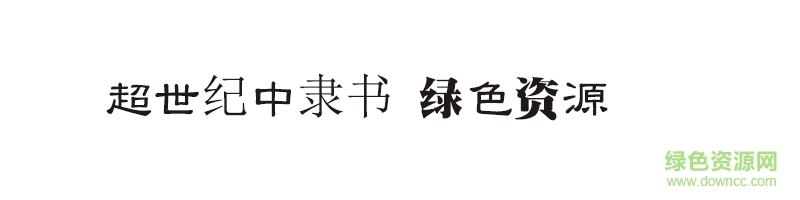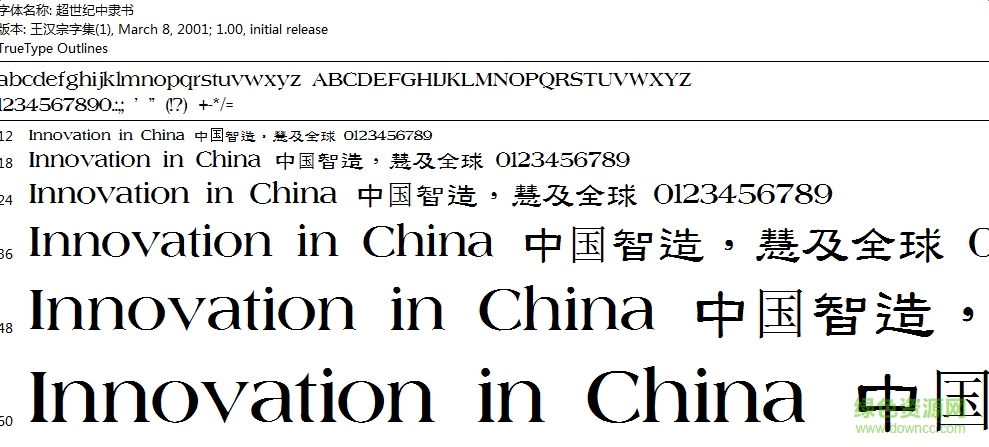
超世紀(jì)中隸字體是一款形體勻逼齊整、字體比較容易書寫的標(biāo)準(zhǔn)字體。它是大篆由隸、楷之間的過渡而來,非常受用戶的喜愛!對(duì)自己寫字字體不滿意的朋友們可以來綠色資源網(wǎng)下載哦!
超世紀(jì)中隸書是手寫風(fēng)格的個(gè)性化書法字體,該字體整體效果十分出色,適合應(yīng)用于廣告設(shè)計(jì)、名片設(shè)計(jì)、包裝印刷、產(chǎn)品設(shè)計(jì)等應(yīng)用。